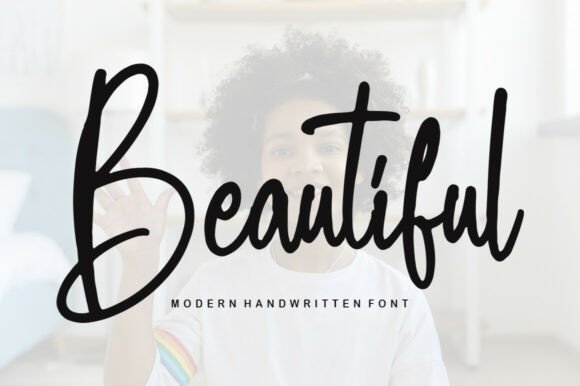
Beautiful
Ulasan lengkap tentang font Beautiful – Sentuhan Elegan untuk setiap karya
Si vous cherchez une police qui combine élégance et modernité, ne cherchez plus : Beautiful est la réponse à toutes vos attentes créatives. Cette police script, à la fois gorgeous et trendy, transforme instantanément n’importe quel projet en une véritable œuvre d’art visuel.
Pourquoi choisir Beautiful ?
- Design raffiné – Chaque glyphe a été soigneusement dessiné pour offrir une fluidité naturelle, idéale pour les titres, les invitations ou les logos.
- Style à la mode – La tendance actuelle des typographies manuscrites se retrouve parfaitement dans Beautiful, apportant une touche contemporaine à vos créations.
- Polyvalence – Parfaite pour le branding, les cartes de visite, les affiches, les publications sur les réseaux sociaux ou même les projets web.
Expérience utilisateur – Ce que disent les créatifs
Les designers qui ont testé Beautiful soulignent immédiatement son impact visuel : « Beautiful donne à chaque mot une présence majestueuse, tout en restant lisible. Les swashes intégrés sont un vrai plus pour personnaliser les premières lettres ». Cette police se démarque également par sa stabilité cross‑platform, garantissant le même rendu sur Windows et macOS.
Conseils d’utilisation pour maximiser l’effet « Beautiful »
- Utilisez des tailles de police supérieures à 48 pt pour mettre en valeur les détails des swashes.
- Associez‑la à une police sans‑serif neutre (ex. : Montserrat, Open Sans) pour créer un contraste élégant.
- Jouez avec les couleurs pastel ou or métallique afin de renforcer le côté « gorgeous » de la typographie.
Conclusion – Beautiful, le choix incontournable
En résumé, Beautiful n’est pas simplement une police script, c’est une déclaration de style. Son design sophistiqué, son encodage PUA complet et sa facilité d’intégration en font le compagnon idéal pour tous les créateurs désireux d’ajouter une touche luxueuse à leurs projets. Faites le choix de la beauté dès aujourd’hui et voyez vos créations s’élever au rang d’œuvres d’art.